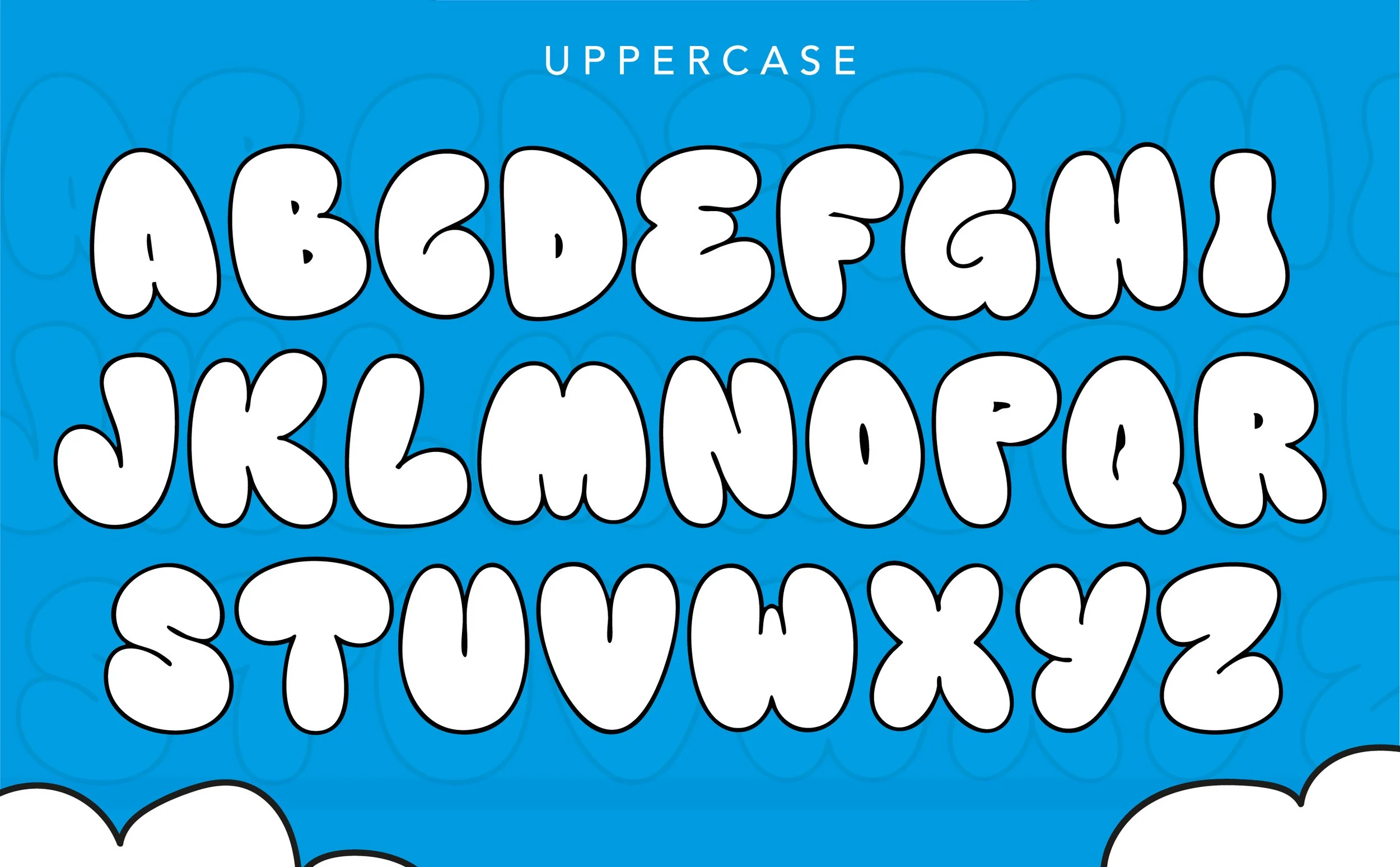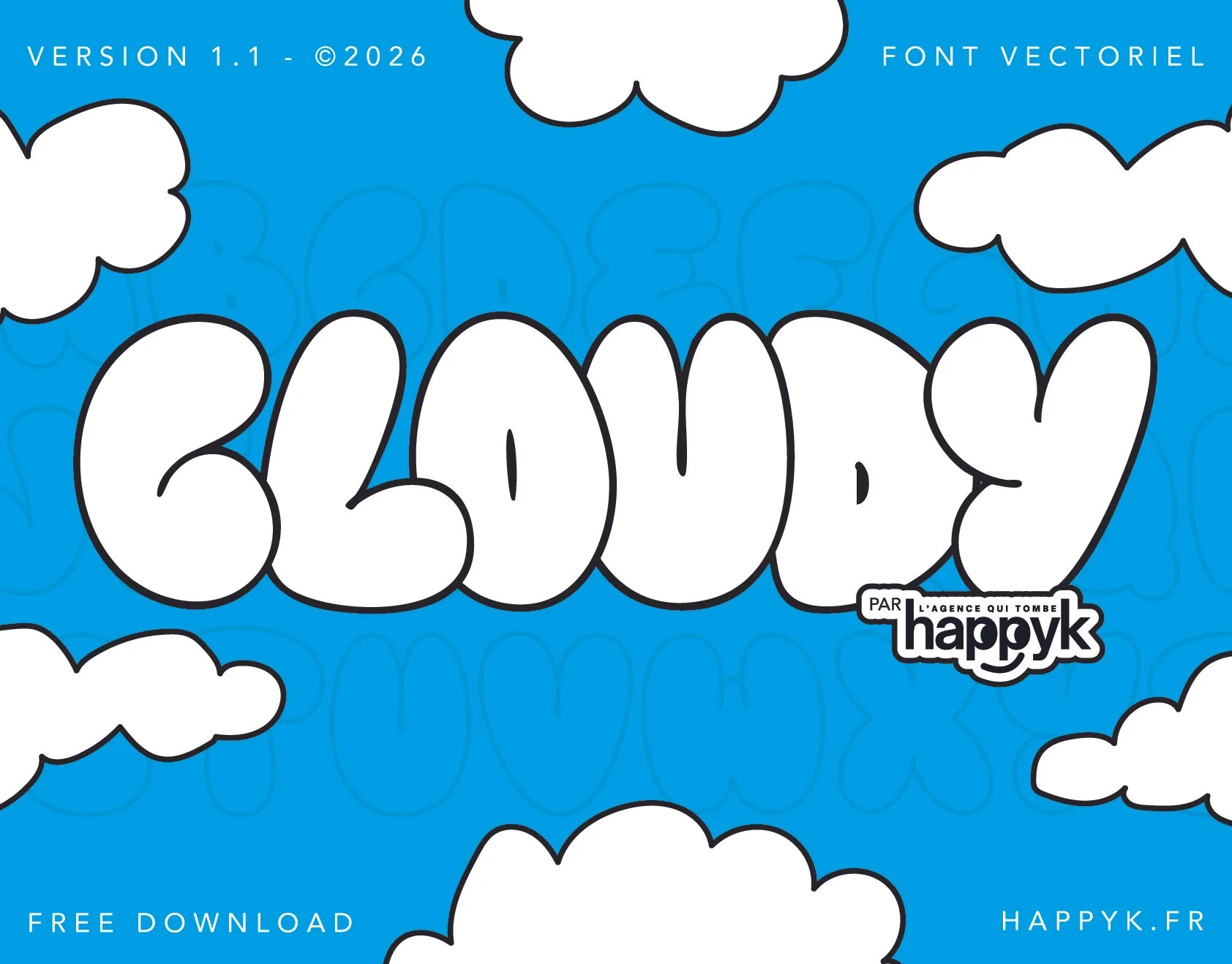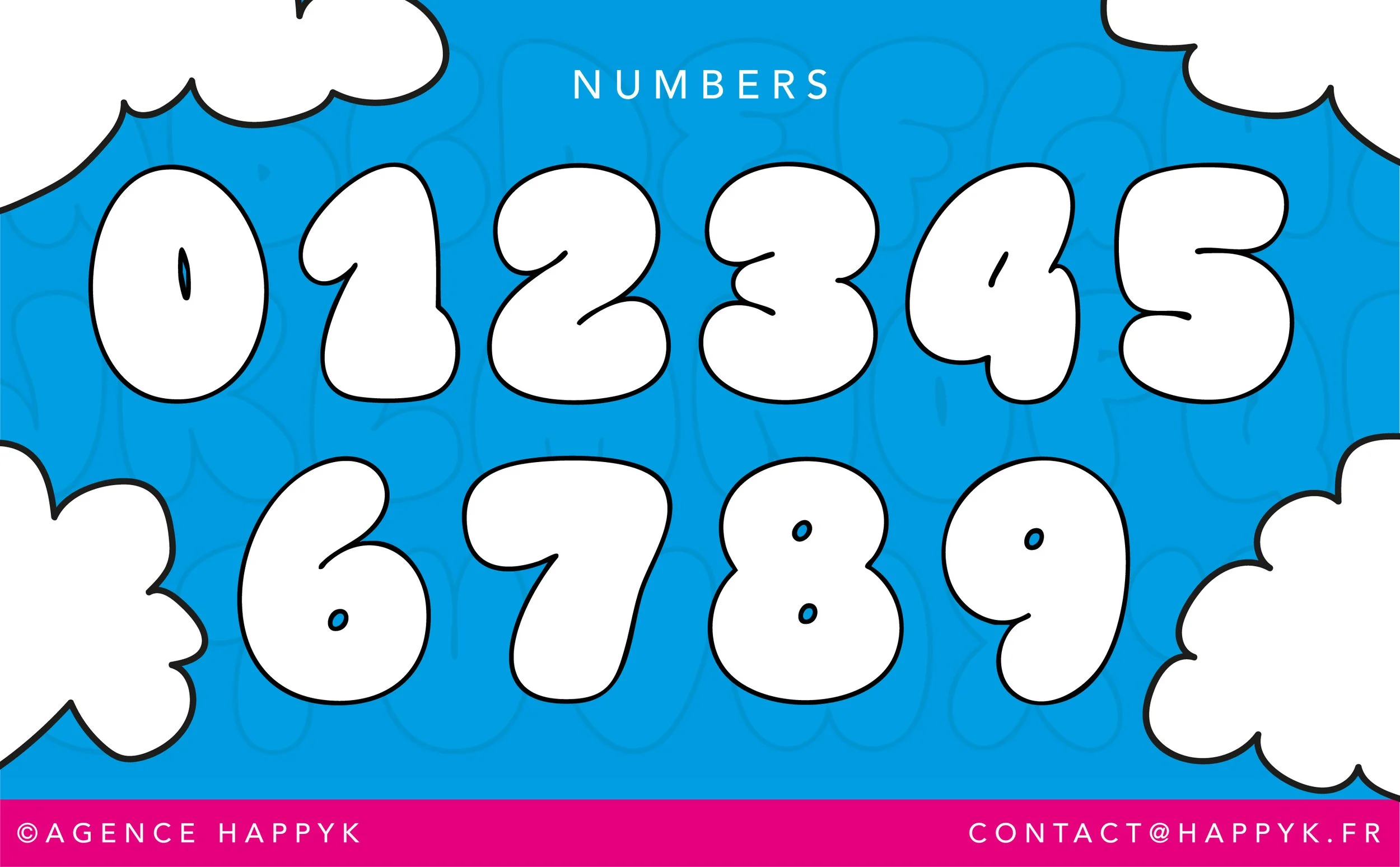
CLOUDY
Douce comme un nuage, visible comme une enseigne.
Cloudy est une typographie ronde, généreuse et rassurante. Son style ludique lui permet d’être utilisée aussi bien pour des projets jeunesse que pour des marques qui souhaitent afficher une personnalité accessible et sympathique. Simple, lisible et attachante, elle fait partie de ces typographies qui donnent le sourire avant même d’avoir commencé à lire. Parfaite pour : Jeux, jeunesse, logos, stickers, merchandising,